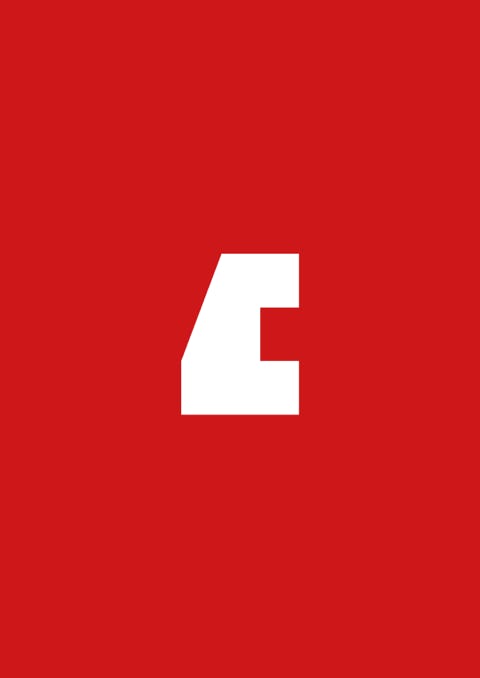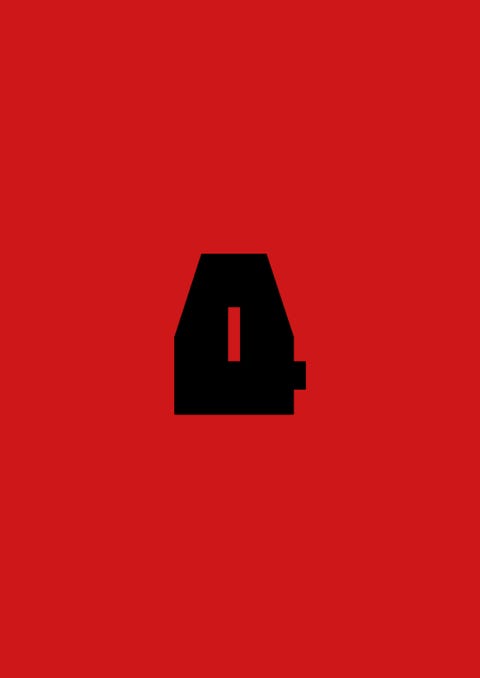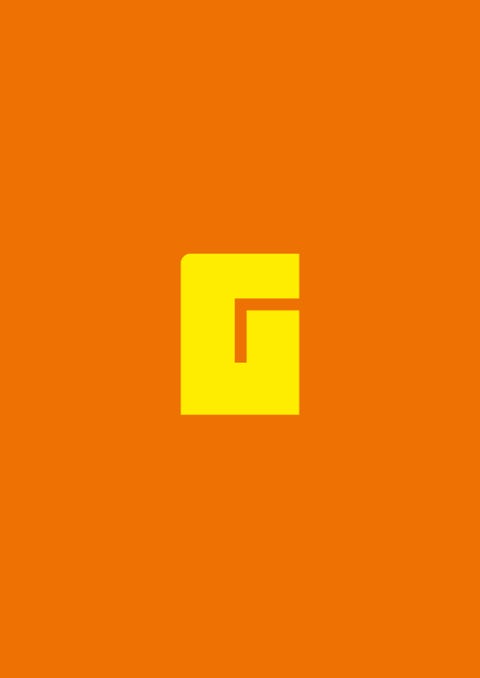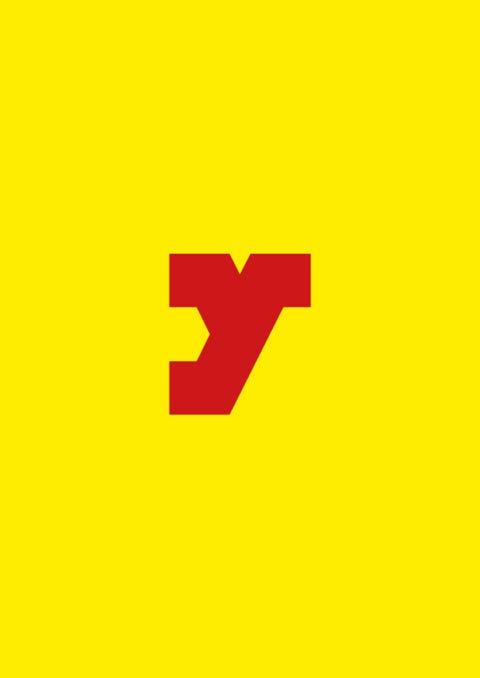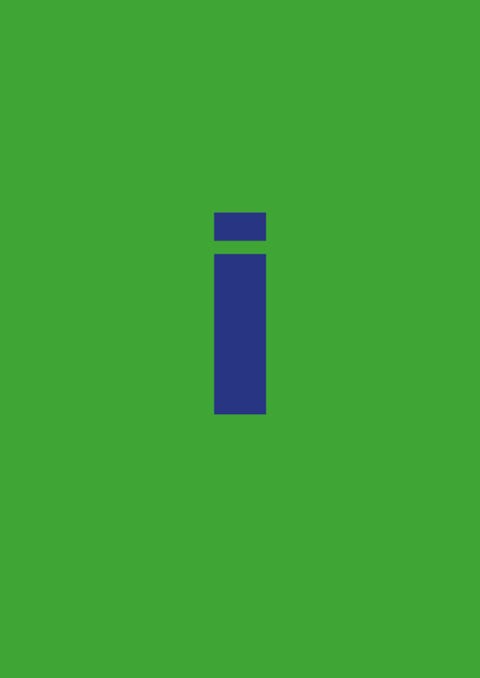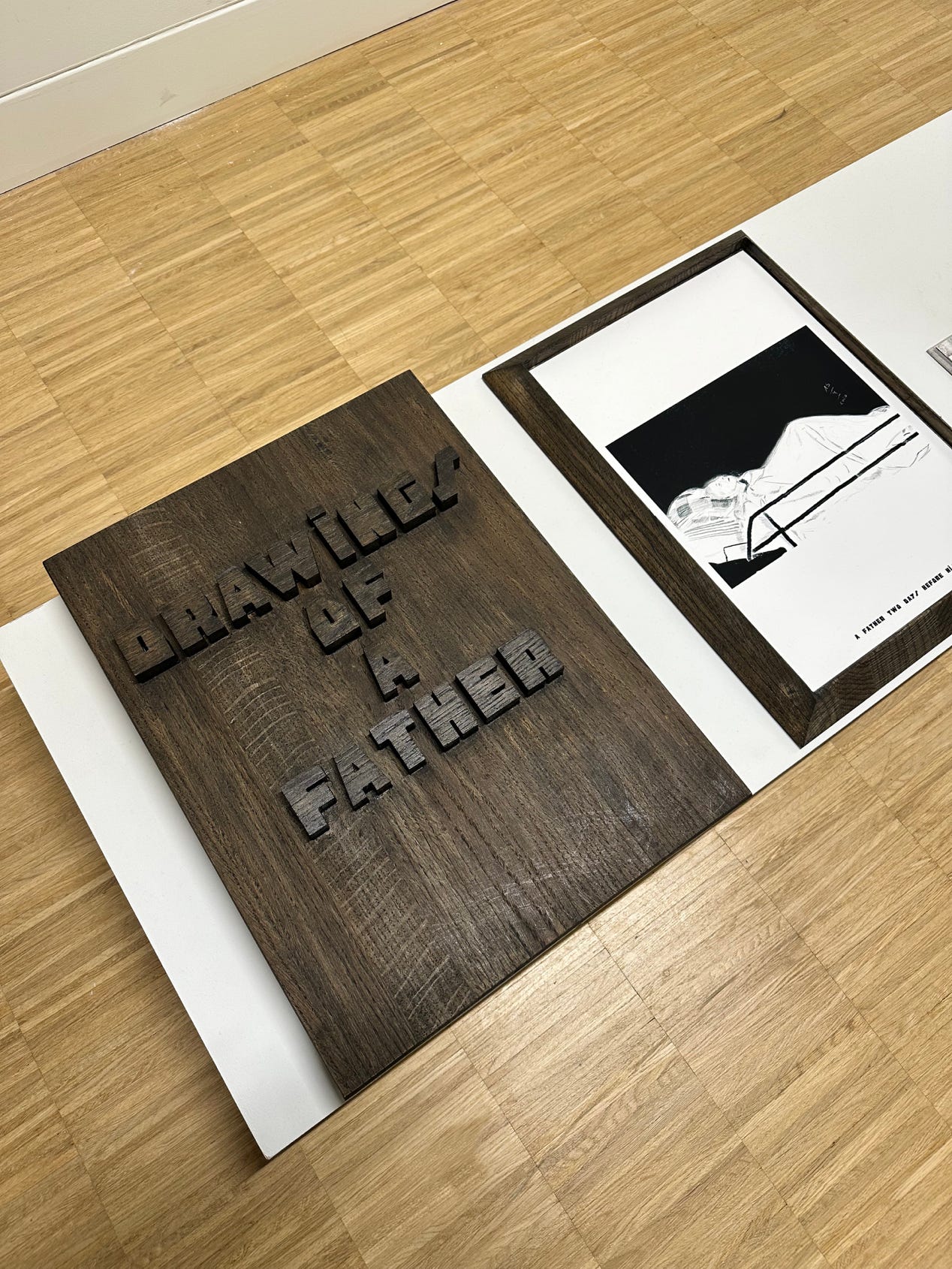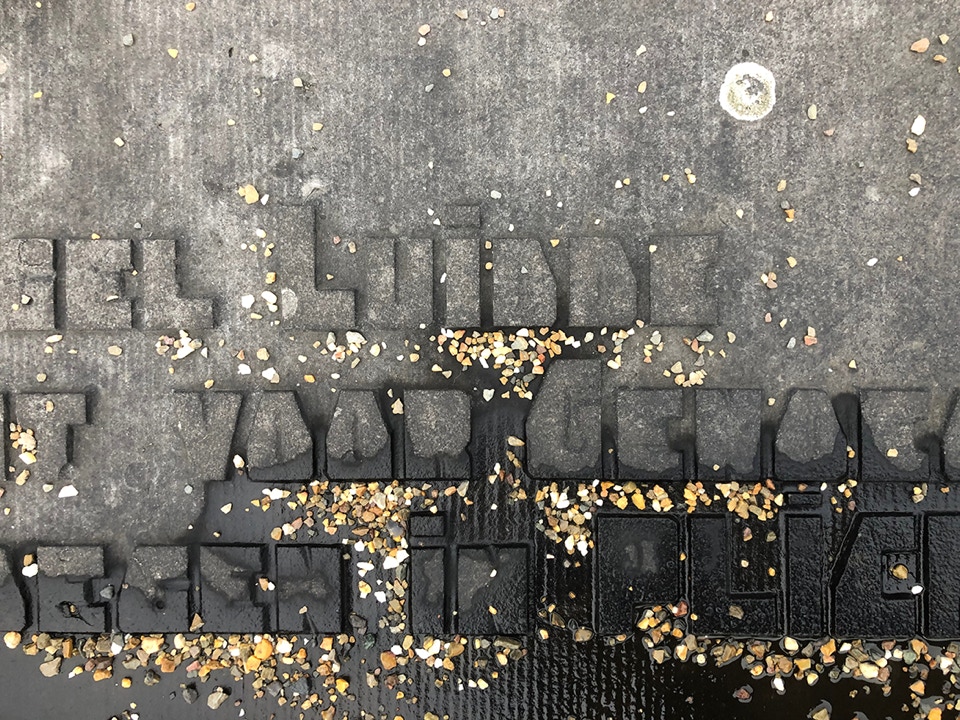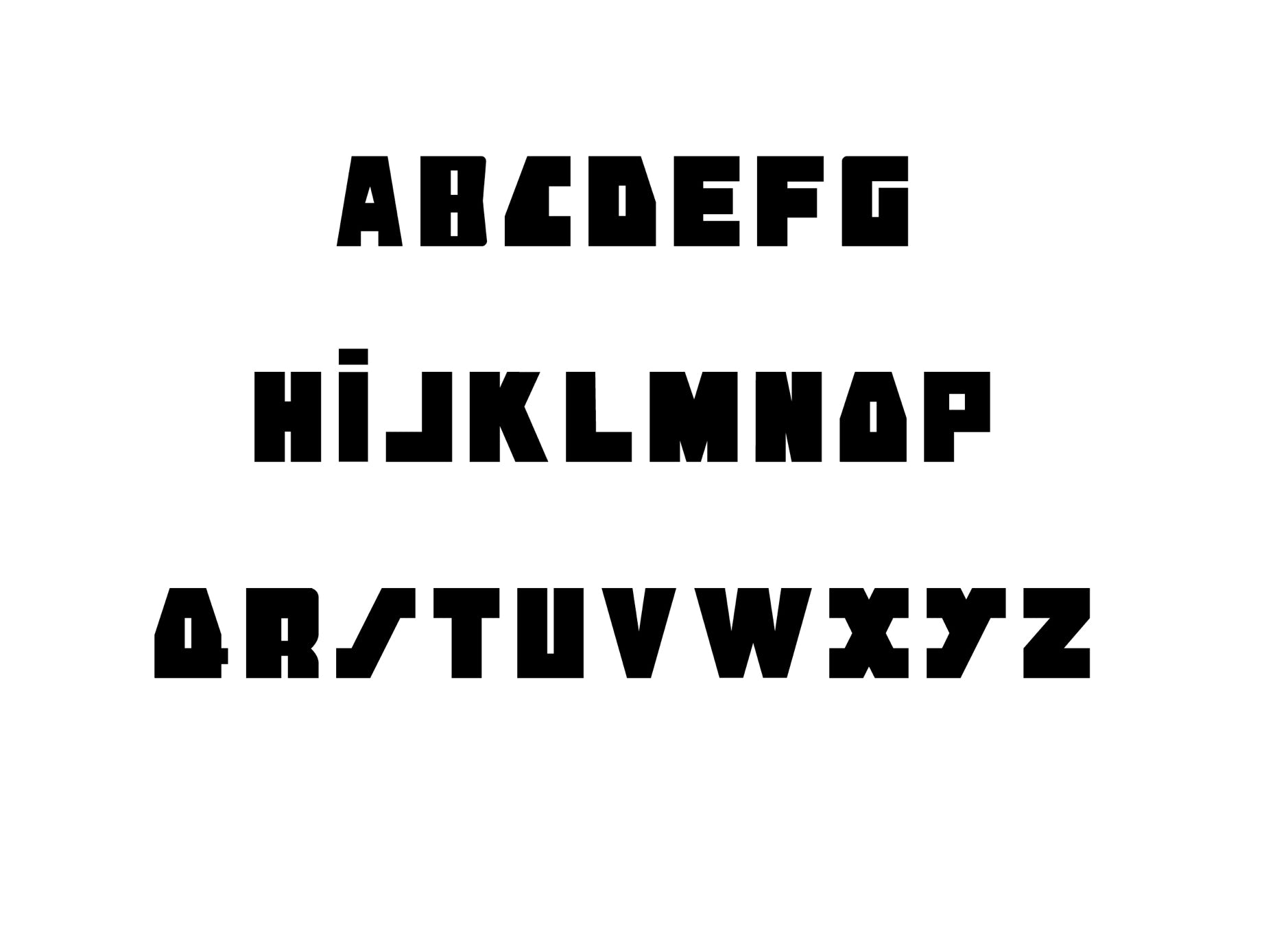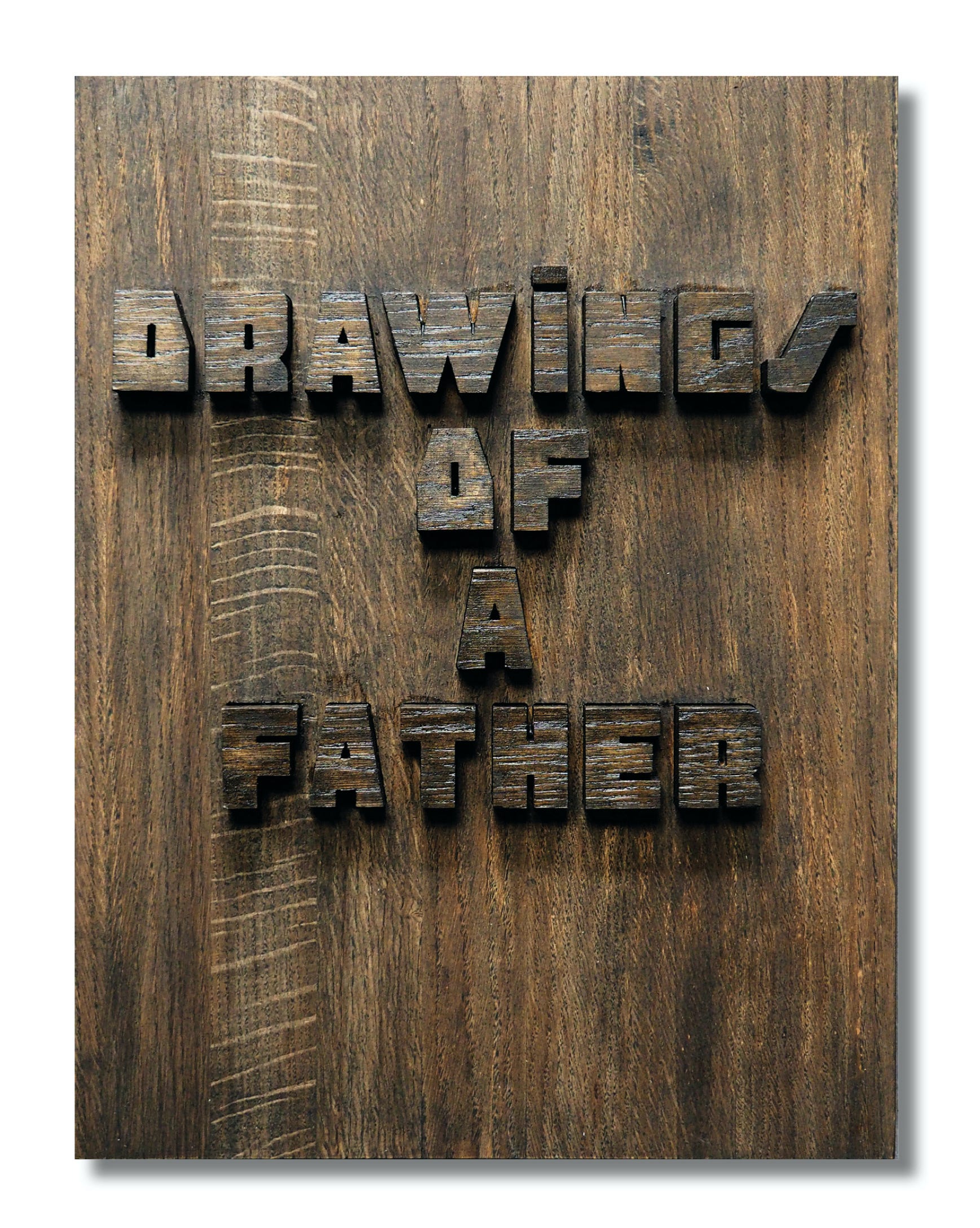
Fröbel, Letters op een grafsteen in Hasselt / Font found on a gravestone in Hasselt
Drawings of a Father, wooden box made for the exhibition In Absence, 2023